まだ、平成? もう、ええわ(令和)!とか言わずに「令和」の書体見本・合字および各フォントベンダーの「令和」対応状況
平成という時代が終わり、令和という時代が訪れている。
そこで新たな元号「令和」という文字に関してのフォントベンダーの対応状況をまとめてみた。
みんな違って、みんないい!令という文字に関しての書体による「令」の字形違いについて
「令」という文字の字形の違いついて、よく話題になっているが、上記のとおり、明朝体と楷書体などで「令」という文字の字形は異なっている。
こうした明朝体と楷書体などの字形の違いは、字体としては同じ文字でも、明朝体活字の形と筆写の楷書の形との間にある印刷上の書体と手書き上の書体としての習慣の相違に基づく表現の違いによるもの。つまりどちらの書き方のみが正解とというわけではなく、みんな違ってみんなよい、無問題なのだ。
文科省によると、手書き文字の形は多様であり、その文字としての骨組みが認められるのであれば、細部の違いによって誤りと判断すべきではないという見解になっている。
草書体/くずし字:崩し字「令和」書体見本
行書体「令和」書体見本
篆書体「令和」書体見本
古印体「令和」書体見本
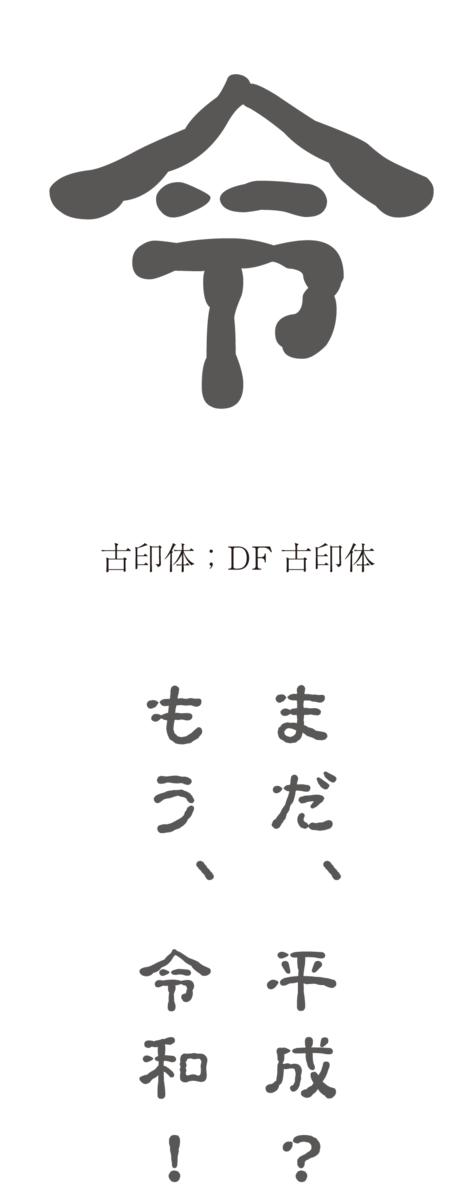
楷書体「令和」書体見本
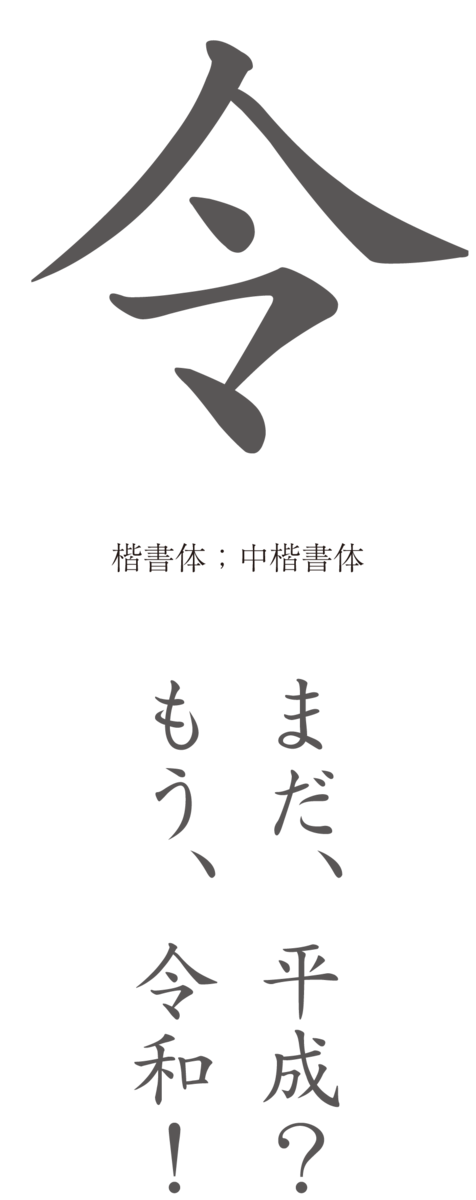
教科書体「令和」書体見本
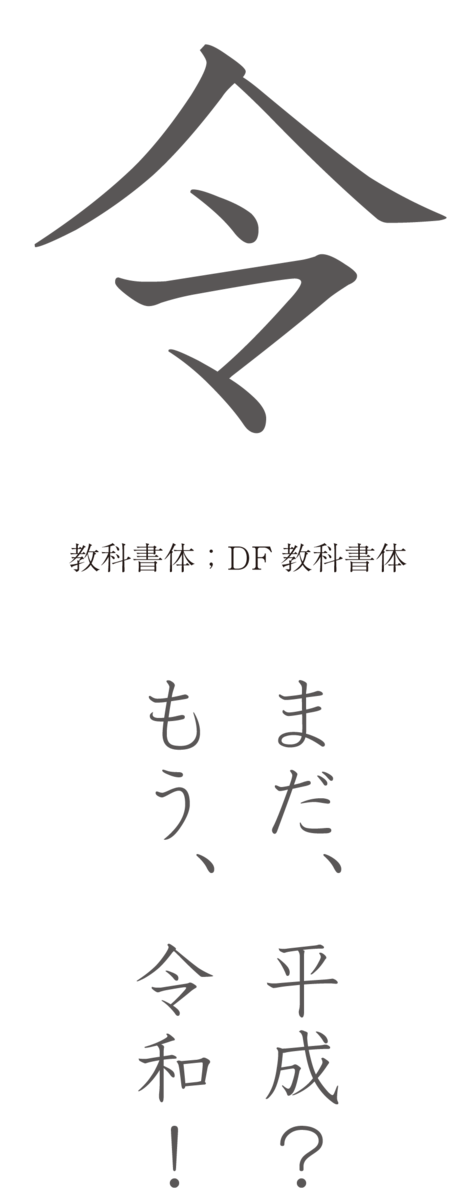
UD教科書体「令和」書体見本
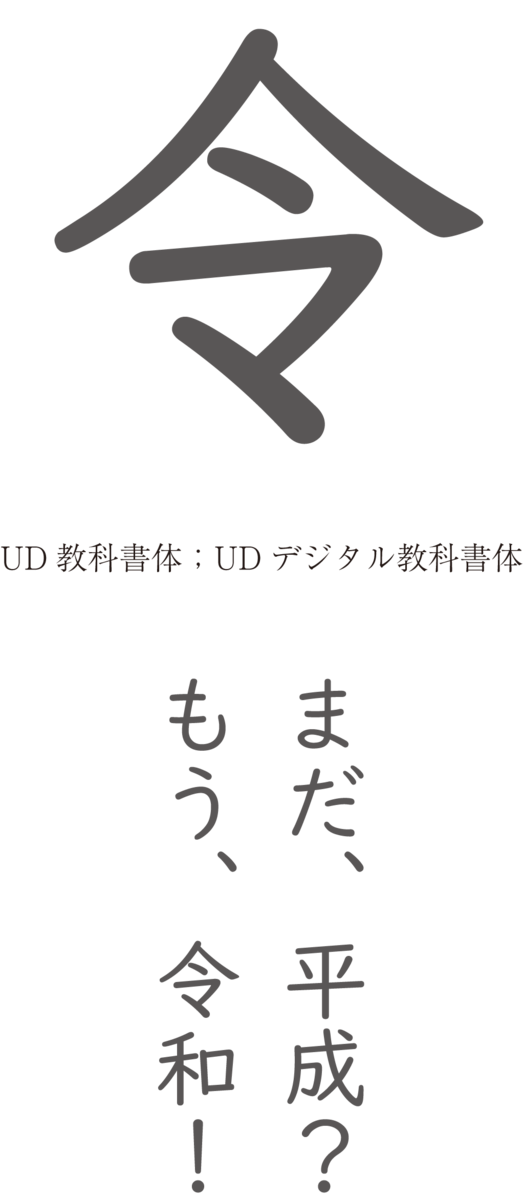
隷書体「令和」書体見本
明朝体「令和」書体見本
UD明朝体「令和」書体見本
ゴシック体「令和」書体見本
丸ゴシック体「令和」書体見本
UDゴシック体「令和」書体見本
UD丸ゴシック体「令和」書体見本
江戸文字/勘亭流(芝居文字)「令和」書体見本
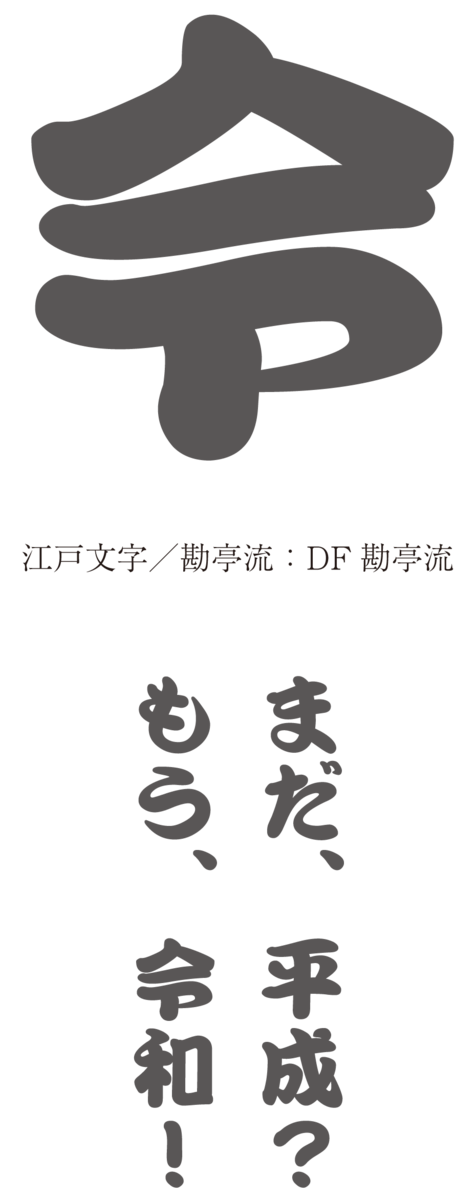
江戸文字/相撲字「令和」書体見本
江戸文字/籠文字「令和」書体見本
江戸文字/寄席文字「令和」書体見本
江戸文字/髭文字「令和」書体見本
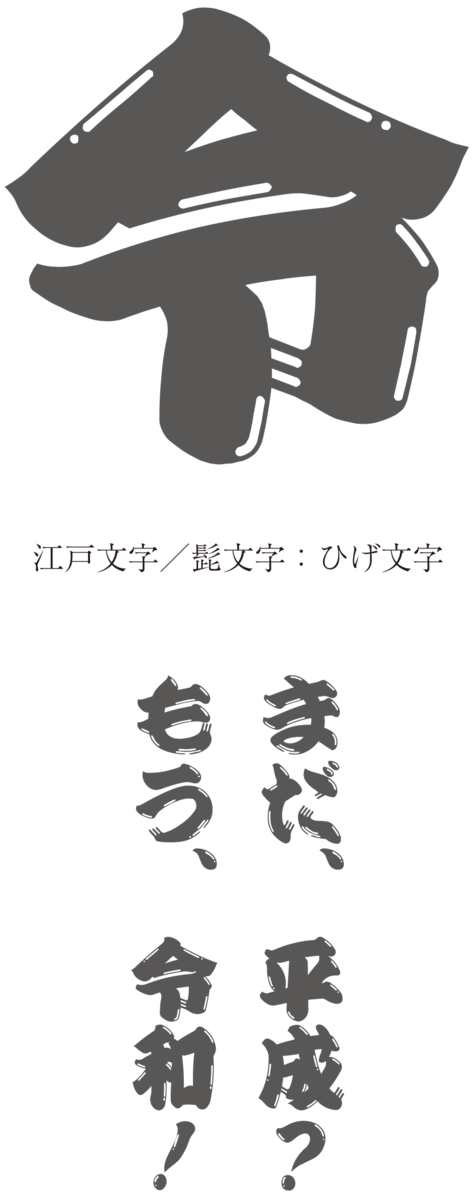
独立行政法人情報処理推進機構(IPA)による商用・非商用に限らず無償で利用できる「IPAexフォント」に令和合字が対応!
独立行政法人情報処理推進機構(IPA)は2019年4月26日に「IPAexフォント」の最新版v004.01を公開。本バージョンでは、新しい元号“令和”の合字(U+32FF“SQUARE ERA NAME REIWA”)が追加実装された。
「IPAexフォント」には明朝体の「IPAex明朝」とゴシック体の「IPAexゴシック」があり、“U+32FF”を入力すればどちらのフォントでも令和の合字を使用できる。
Adobe Fonts / アドビシステムズ
アドビ システムズは2019年4月1日に、「アドビ、新元号「令和」の合字をAdobe Fontに追加」のお知らせを公式サイトに掲載。
Adobe Fontsの「小塚明朝」「小塚ゴシック」「源ノ角ゴシック」日本語およびPan-CJKフォントで新元号「令和」の合字を追加がなる。
合字は『国際符号化文字集合(UCS)』にも含まれ、日本語フォントやPan-CJKフォントで利用可能で、新元号の合字もU+32FF の文字コードが割り当てられ、UCSに収録の予定です。「令和」の縦組 横組用の2つの合字を作成し、Adobe Fontsから提供するアドビのフォントに段階的に追加していく予定。
2019年4月11日のAdobe Blogで小塚明朝、小塚ゴシック、源ノ角ゴシックのアップデートが完了したことを発表している。
ダイナフォント / ダイナコムウェア
ダイナフォントを開発・販売するダイナコムウェアは2019年4月3日に、「文字文化を伝えるダイナフォントが、新元号「令和」の合字を日本語全書体に対応。」というお知らせを公式サイトに掲載。
明治・大正・昭和・平成といった元号を構成する2文字を全角1文字に入るように圧縮して設計した「合字」に関して新元号である「令和」も対応し、その対応書体第1弾として4月3日(水)に「金剛黒体」6ウェイト(OpenType Standard N版、OpenType Pro 1-6N版)合計18書体を新元号に先行対応させた事が発表となった。
「金剛黒体」の対応を皮切りに、2019年5月末日までにダイナフォント「DynaFont」シリーズ日本語全書体が新元号に対応させる予定との事。
元号「令和」発表時の“令”の字形に対応した「楷書体 令和版」6書体が2020年6月5日に「DynaSmart V」に収録
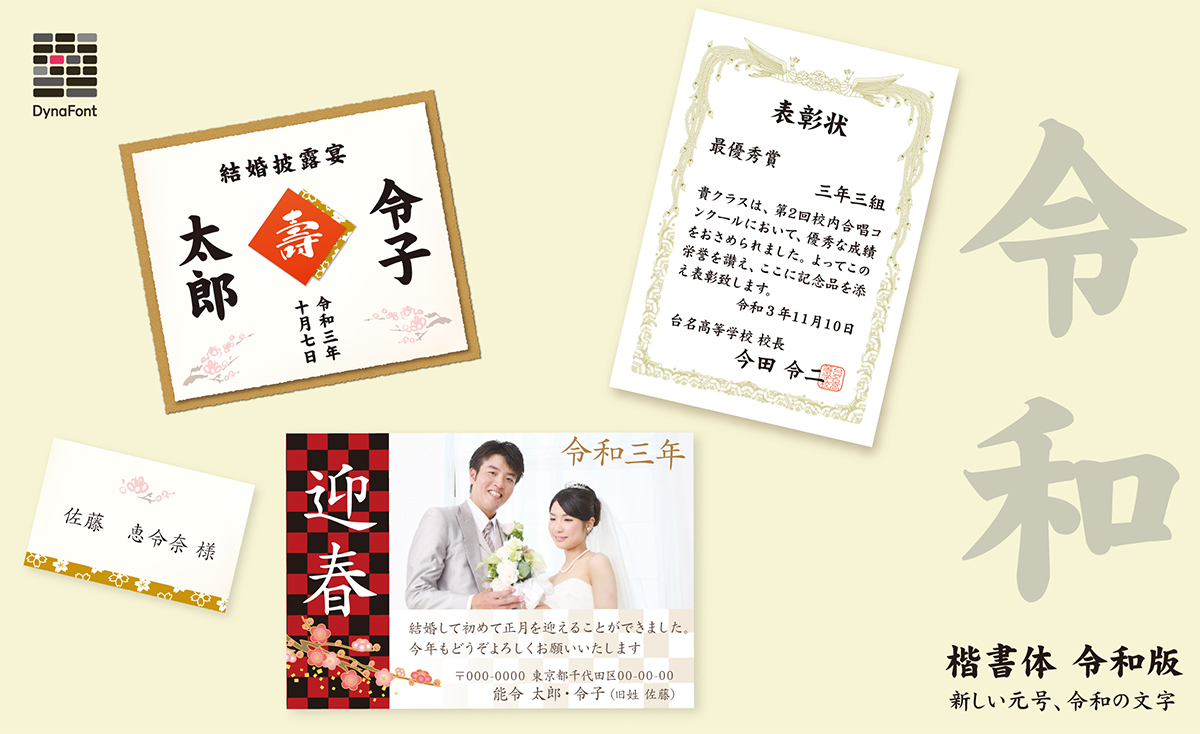
元号「令和」発表時の“令”の字形に対応した「楷書体 令和版」6書体が2020年6月5日に「DynaSmart V」に収録された。
「楷書体 令和版」は、厳格な楷書体を現代でも使いやすいように視認性と判別性を高めたデザインの楷書でる細楷書体、中楷書体、中太楷書体、太楷書体、極太楷書体、超極太楷書体の6書体を元号「令和」発表時の“令”の字形に対応した書体。
字游工房
字游工房は2019年4月8日に『游明朝体ファミリー』『游ゴシック体ファミリー』の正規ユーザーの皆さまへアップデートのお知らせを公式サイトに掲載。
このバージョン2.300へのアップデートで『游明朝体ファミリー』『游ゴシック体ファミリー』に新元号「令和」の合字の追加等を行われている。